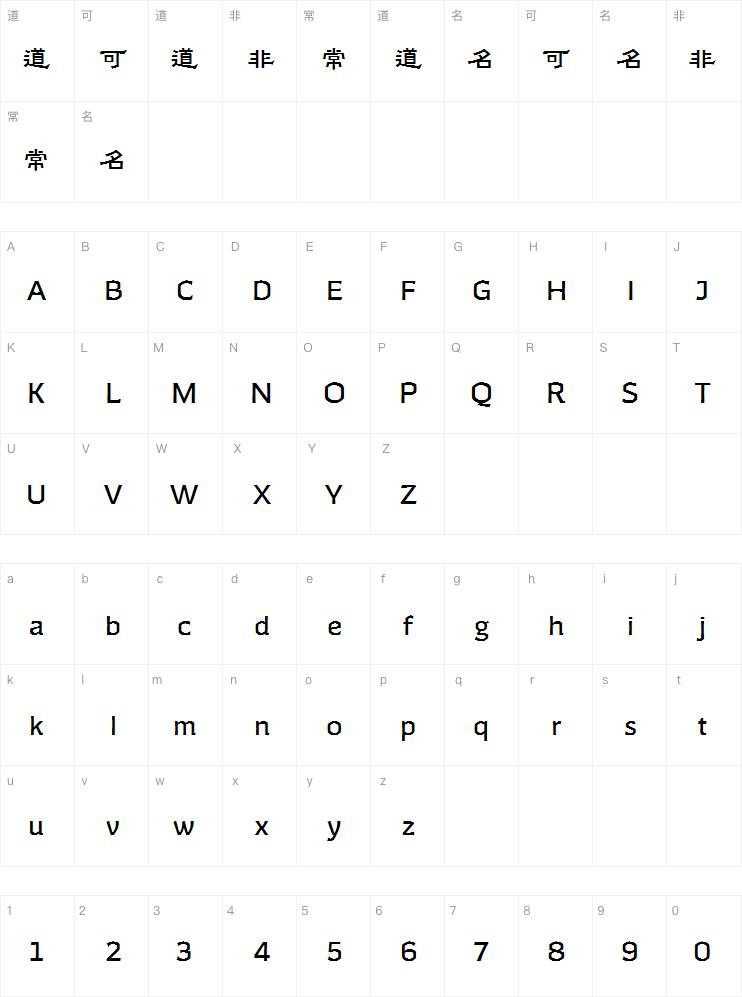
汉仪金石一款具有独特风格的中文字体,整个字体系列包含6个字重,有简体和繁体两个版本系列。这款字体的特点是线条粗犷、结构紧凑,充满了古朴和厚重的气息。它的字形饱满,笔画转折处有明显的棱角,给人一种刚劲有力的感觉。同时,汉仪金石在保持传统韵味的同时,也融入了现代设计元素,使得这款字体既有古典之美,又不失时尚感,适用于各种正式场合的文字排版,如书籍封面、海报标题、标志设计等。